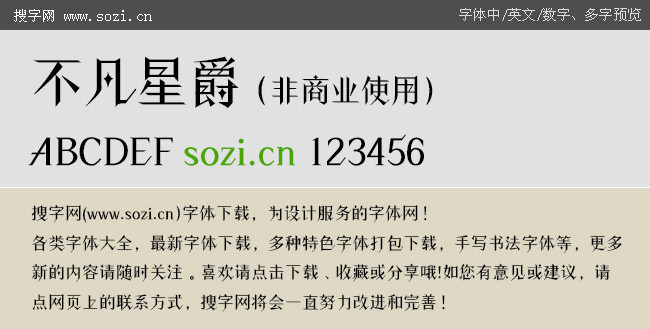
不凡星爵(非商業(yè)使用)
搜字網(wǎng)給大家提供不凡星爵(非商業(yè)使用)中文藝術(shù)字體下載,這是一款非常個性的藝術(shù)字體,字體線條粗壯有力,每一個漢字都帶有星光,適合卡通畫冊、海報(bào)設(shè)計(jì)等廣告設(shè)計(jì)使用(此字體為個人非商用版,如需商用請聯(lián)系作者購買版權(quán))。